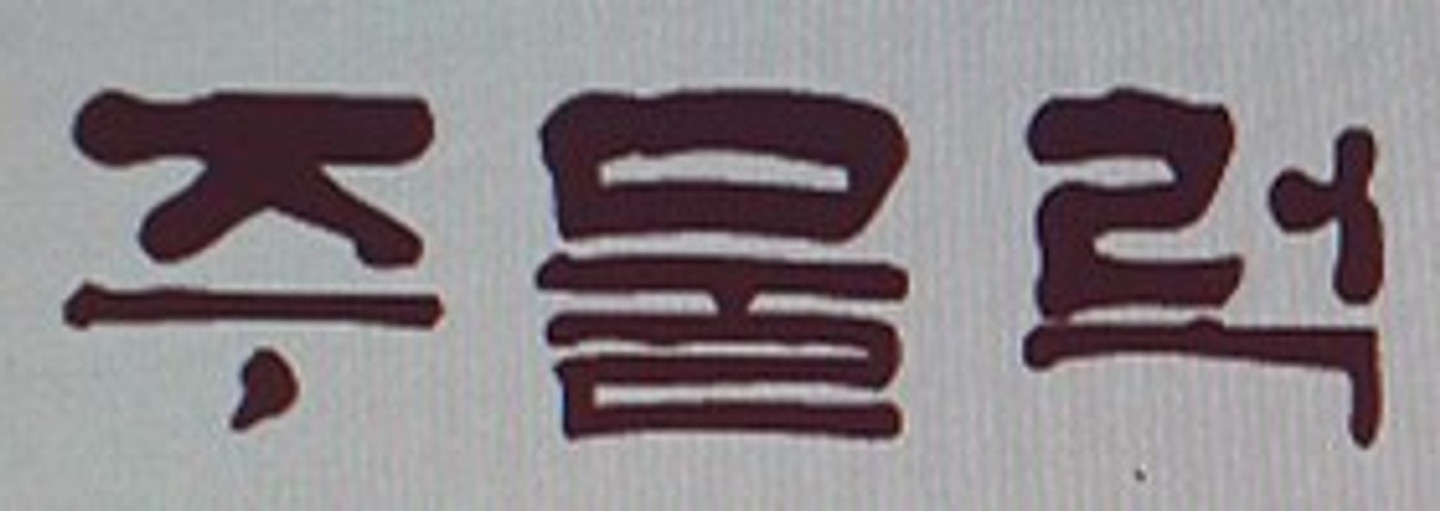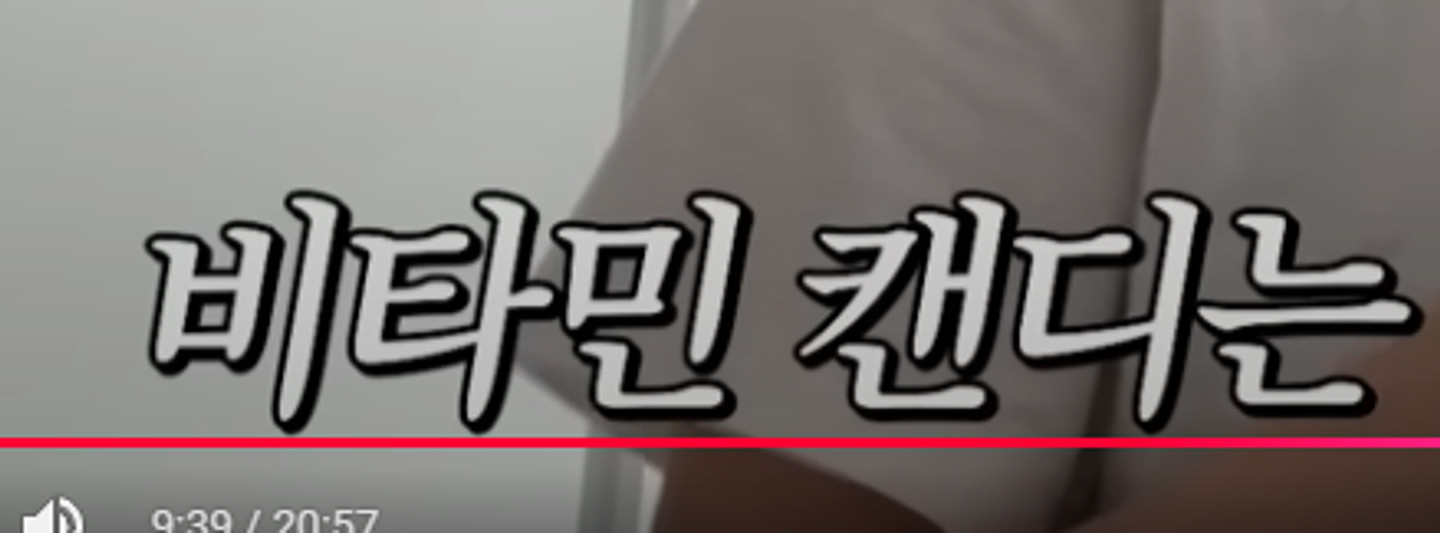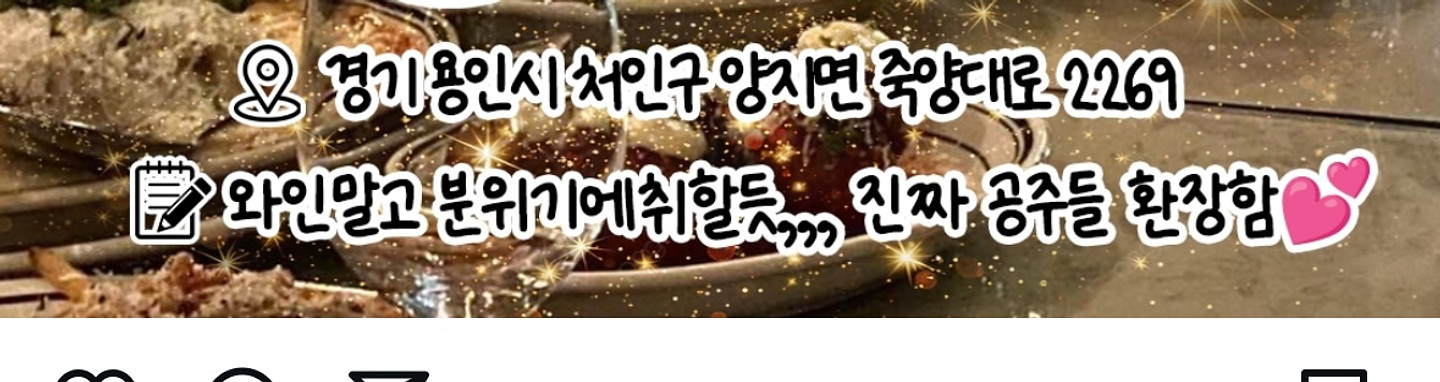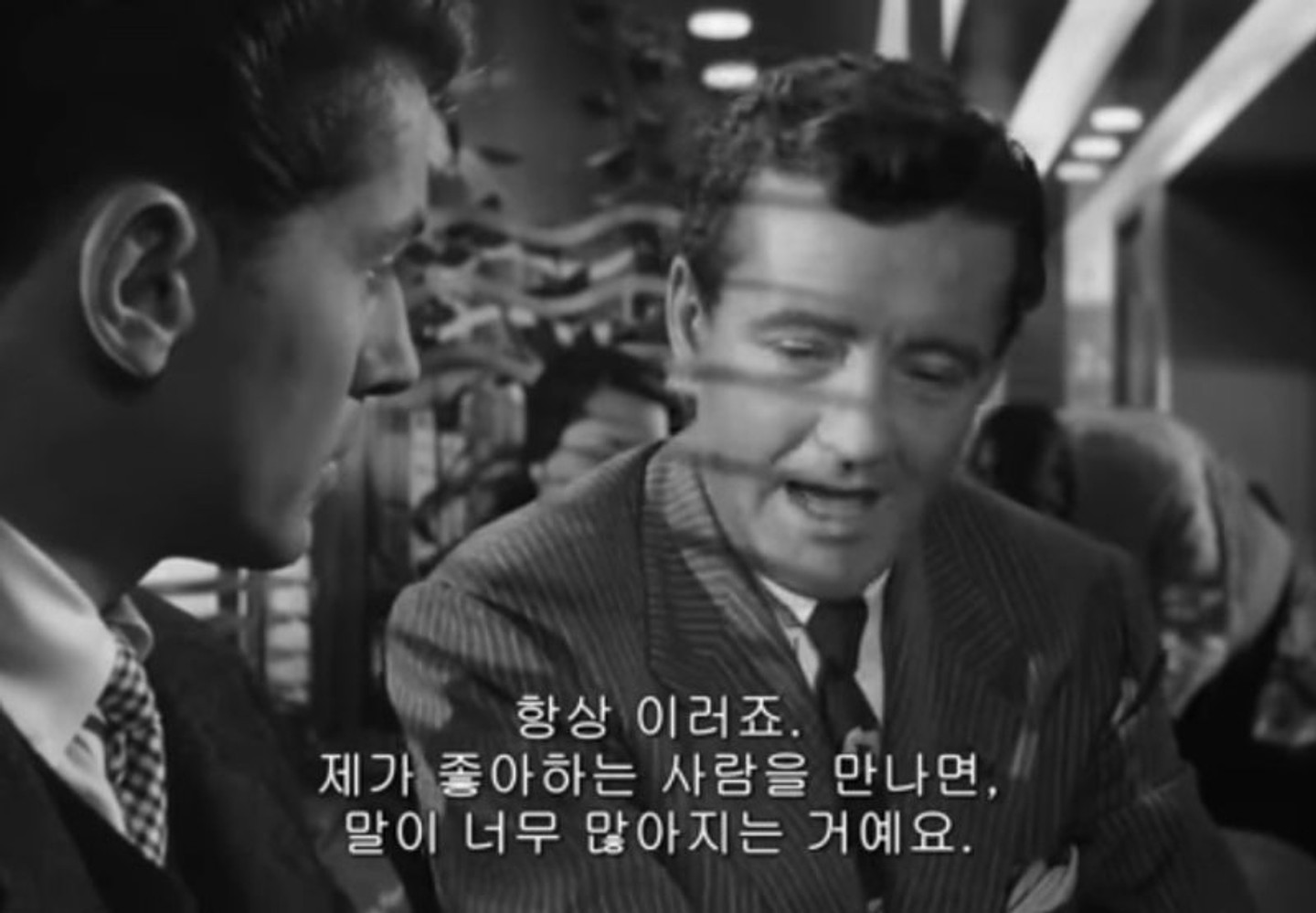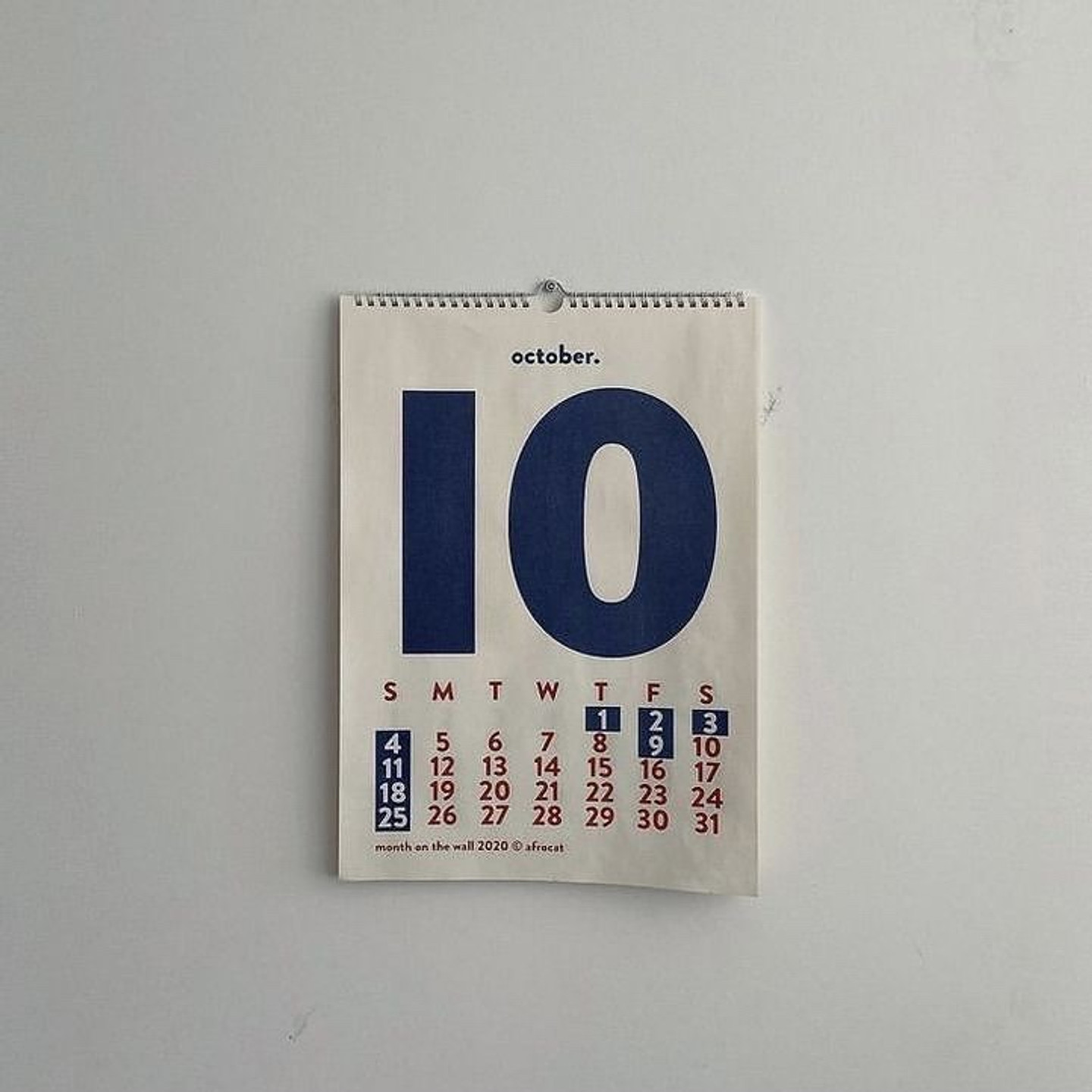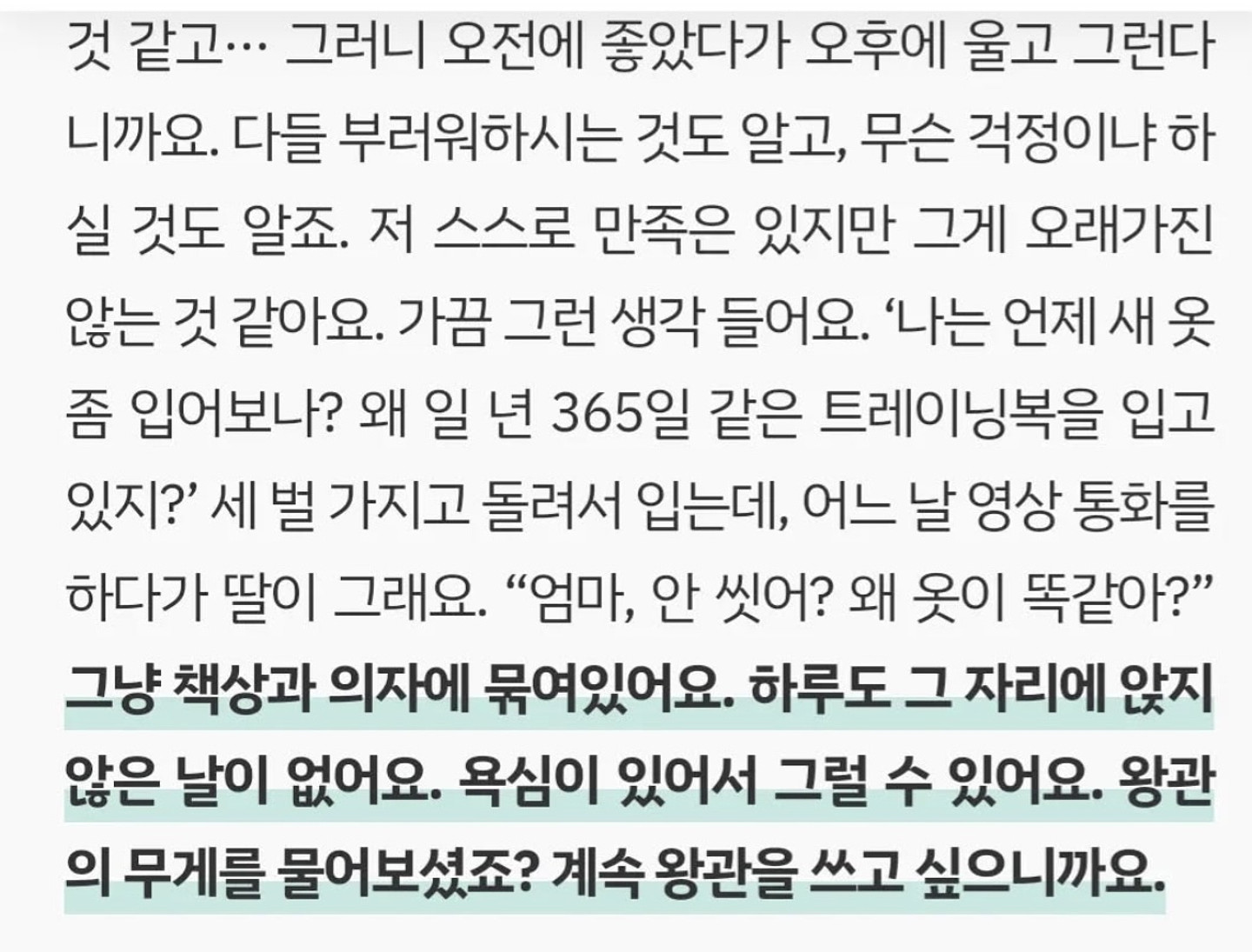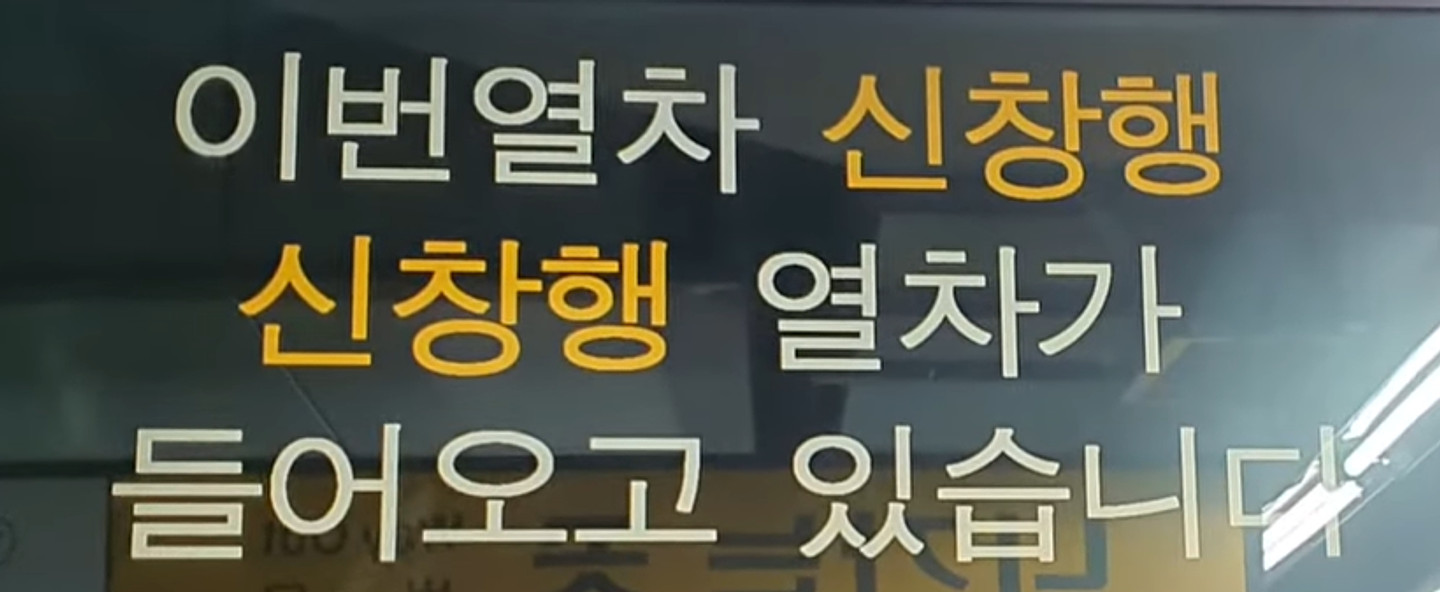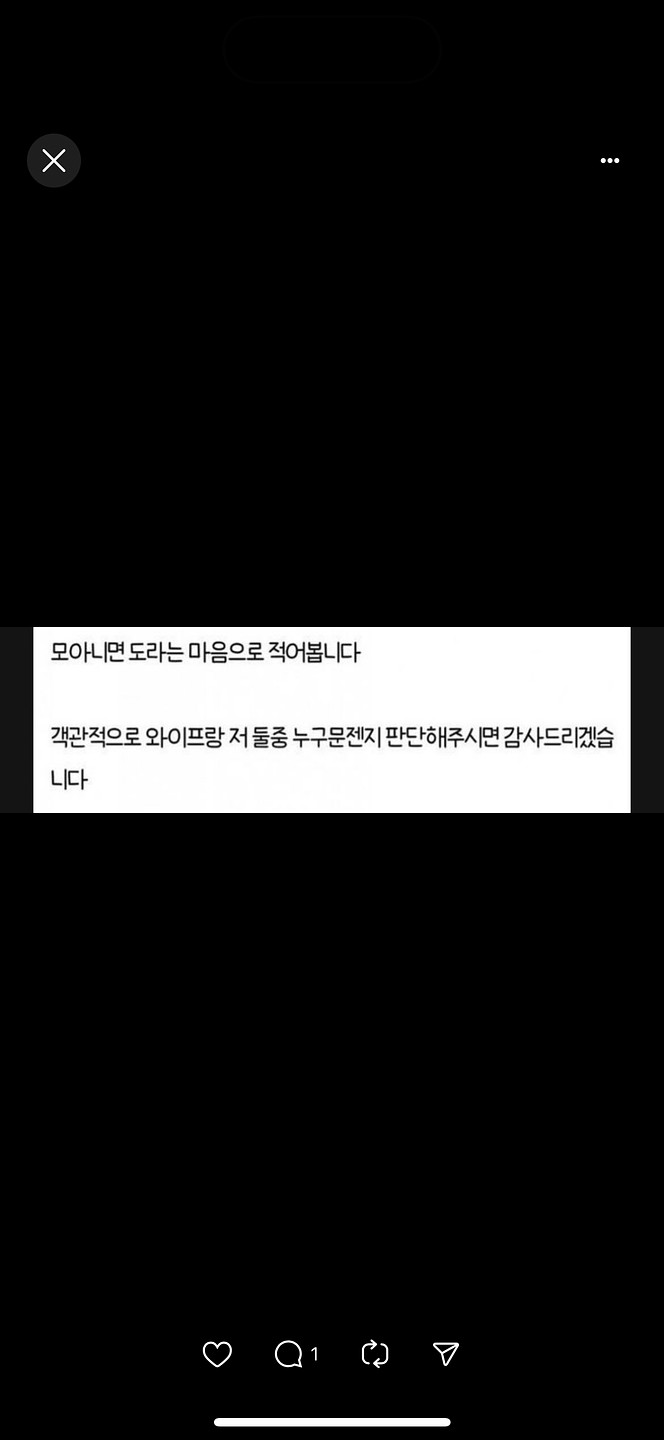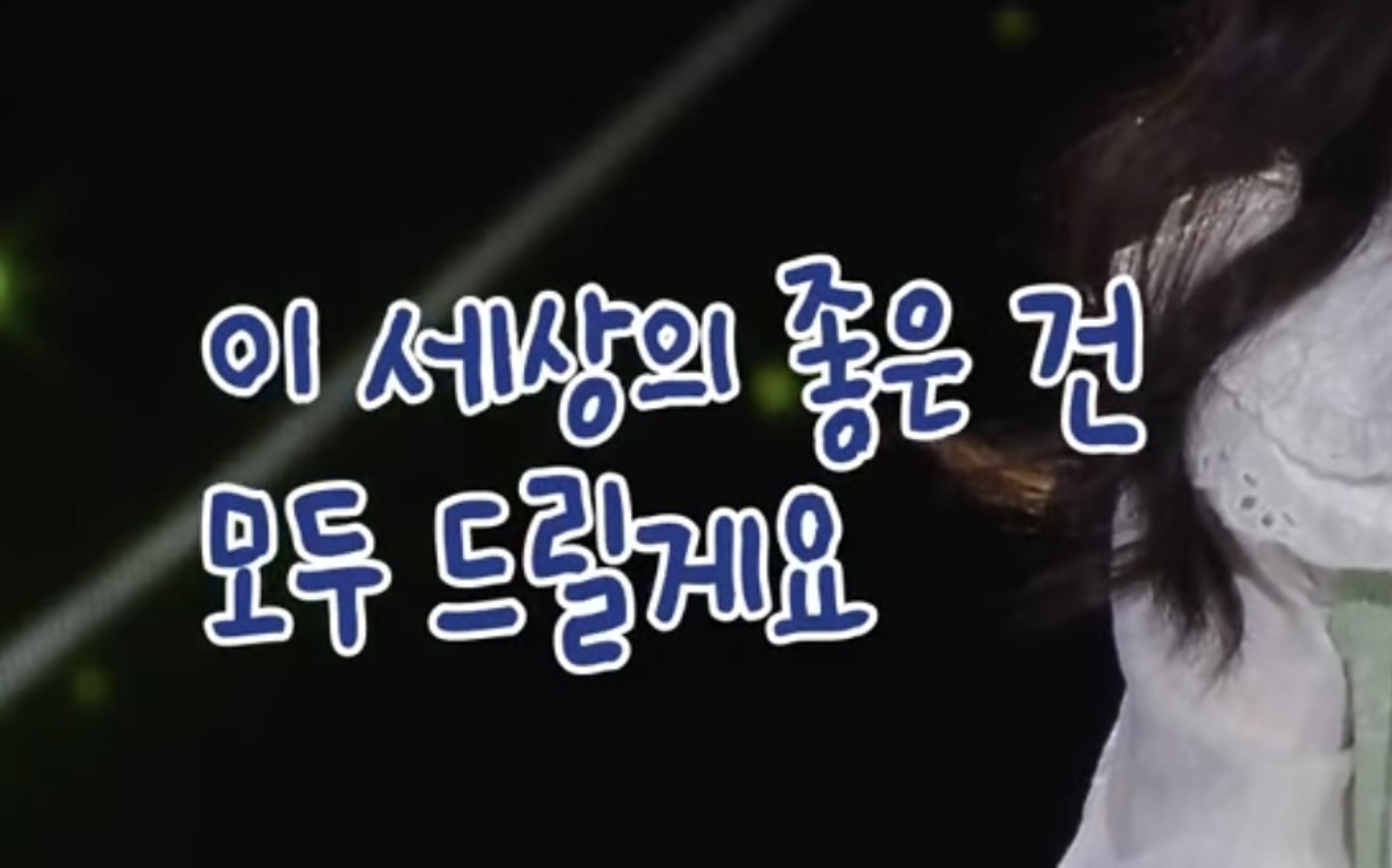
궁금해요 이 글씨체
2호선에서 볼 수 있는 폰트인데 역 이름과 숫자, '내리실 문은 왼쪽입니다'에 쓰인 폰트는 어떤 폰트일까요?
이 폰트 이름 알려주시면 감사하겠습니다!!
이 폰트 뭔가요??
아형에서 나온 폰트인데 이 폰트가 뭔가요?
이 글씨체 뭔지 알 수 있을까요 ㅠㅠ
이 폰트명이 뭘까용,,??
이 폰트 무엇인가요?
갤럭시의 옛날 폰트로 추정됩니다🥹,, 꼭 알고 싶습니다 아시는 분은 정보 부탁드릴게요ㅠㅠ
?
이거 무슨 폰트인가요??ㅠㅠㅠ 너무 궁금해서 잠도 못 자겠어요
어제 문명특급에 나온 자막인데 뭔지 아시는 분 계신가요!?
폰트 이름이 궁금합니다!! 화질이 구려서 죄송합니다.ㅠㅠㅠ
무슨 폰트인지 아시는 분 계신가요.. 프리텐다드 노토산스도 아니고ㅠㅠ 물음표가 독특해서 아무리 찾아도 안 나오더라구요
무슨 폰트인지 궁금합니다~~~
비슷한폰트 찾습니다
폰트 뭔지 궁금해요ㅠ
이런 영어폰트 많이쓰는데 뭘까요?
썸네일에 쓰는 폰트인데 꼭 찾으면 뭔지 모르겠네요... 아시는 분 좀 알려주세요ㅠ
릴스 보다가 눈에 띈 폰트인데 손글씨같은게 특징이에요. 무슨 폰트인지 알 수 있을까요?
사진 속 폰트 어떤건지 궁금합니다ㅠㅠ
이 폰트 뭔지 아시는 분 있나요....?
해은님 유튜브에 나오는 자막 폰트 넘 궁금해요ㅠㅠ 썸네일로도 이 폰트 쓰시던데..
본문 폰트 궁금해요
한글 폰트 알려주세요
이거 어떤 폰트 인가요...?
이 폰트 어떤 폰트 인가요?
이 폰트가 뭘까용... 타 사이트 AI폰트검색 서비스 다 돌려봣는데 다른 유료폰트를 추천해주는데 비슷하지도 않네요 ㅠㅠ
가운데 파란색 폰트 궁금해요
로고 한글, 영어 서체 모두 궁금해요!
이 기본 폰트 뭔가요?? 막상 찾으려니 뭔지 모르겠네요
비슷한 글씨체 알수있을까요 soap-regular랑 비슷하게 생긴거같긴 한데 묘하게 길쭉하네요..
무슨 폰트인가요,,?
'윤슬'의 한글 폰트가 무엇인지 너무 궁금합니다!
아는 폰트였는데... 폰트 이름이 뭘까요 ㅠ
이 폰트가 뭘까요..?ㅠㅠ '수' '검' '실'이 특이한데 아무리 찾아도 동일한 폰트를 못찾겠어요.. ㅠ 일단 수박화체, 카페24 아네모네 에어가 비슷하긴 했습니다!
폰트 궁금해요..ㅠㅠ
무슨폰트일까요. 유튜브채널 썸네일입니다
이 폰트 먼가여 ㅠㅜㅜ??
제발제발...이 폰트 어떤거인지 부탁드립니다....
짱오락실에 사용된 한글 폰트체가 궁굼합니다.
많이 보던 폰트인데 산돌구름에서 검색에도 안뜨길래 올려봅니다 도움 부탁드려요 ㅠ.ㅠ
회사명 폰트가 어떤거일까요? ㅠㅠ
이 폰트 이름 궁금해요!!!
손글씨 느낌의 이 폰트 궁금합니다.
저런류의 폰트가 많이보이는데 산토끼체는 아닌거같고 어떤폰트인지 검색해도 안나오네요...너무궁금합니다.
산돌에서 찾아봐도 안 나와서 도움 구합니다. 도저히 모르겠어요...
본문 폰트 아시는 분 계신가요? (사람 속~재능이었다) 폰트 찾는 사이트에서 이미지 돌려 봐도 나오지를 않아서 ㅠㅠ 이쪽에도 올려 봅니다...
궁금핮니다
알려주세요유
이 영어 폰트 뭔가요?
인스타그램 기본 폰트입니다. 혹시 아시는 분 계실까요?
이거 무슨 폰트인가요 자간이 좁혀진 폰트입니더
제목이랑 내용 폰트 무엇인가요?